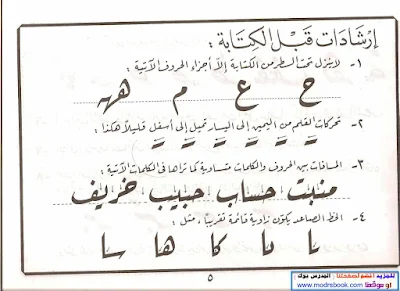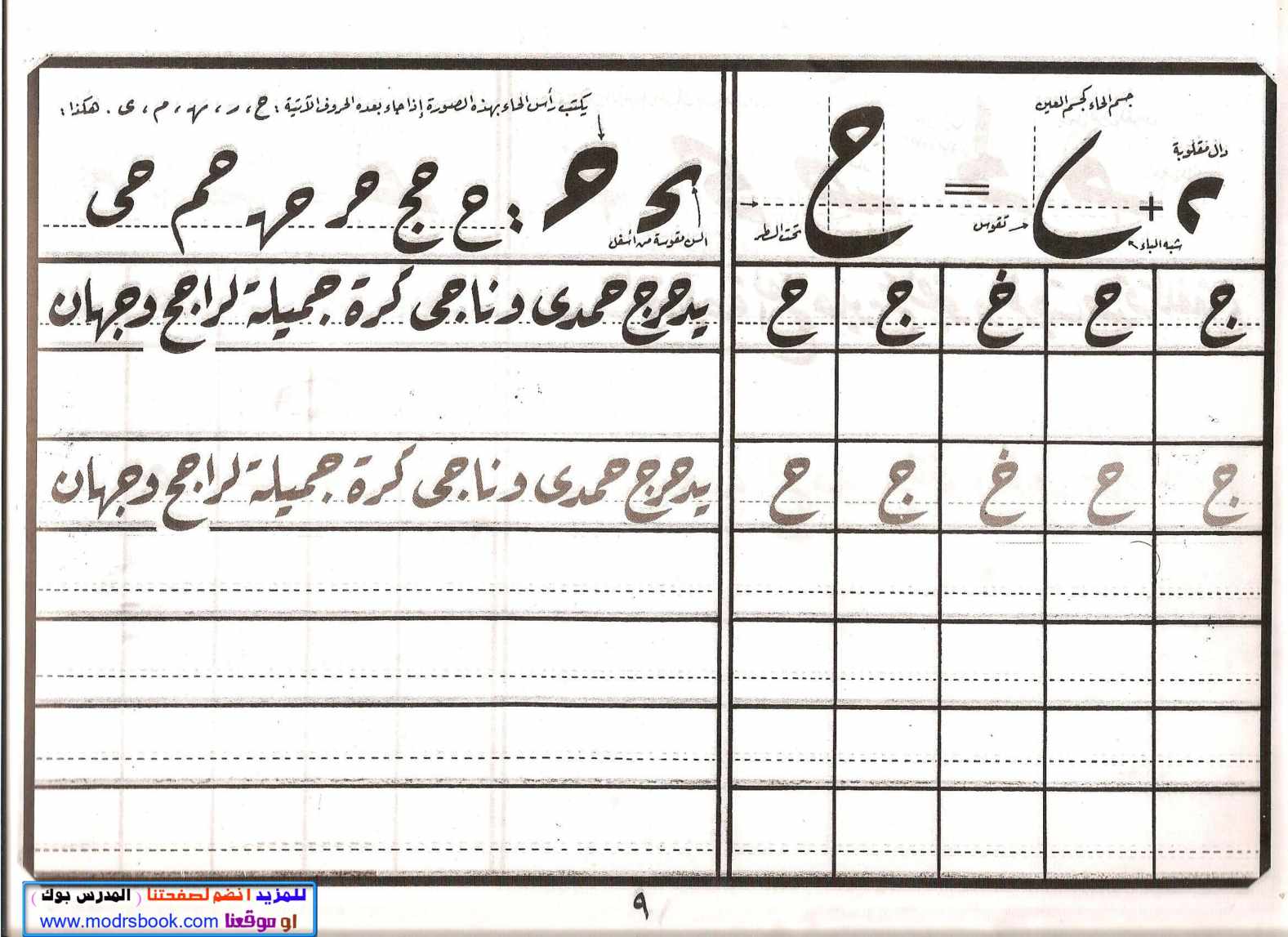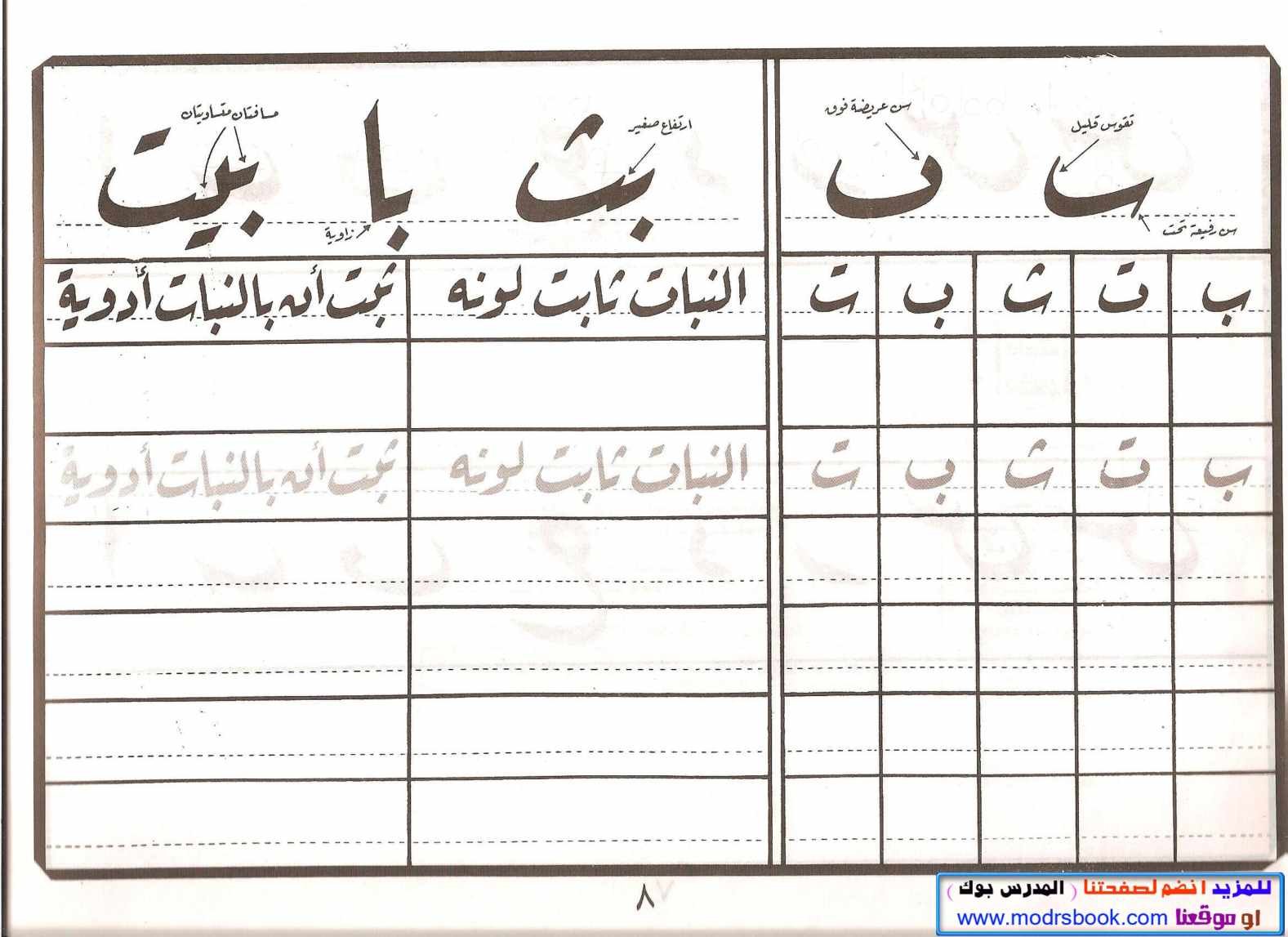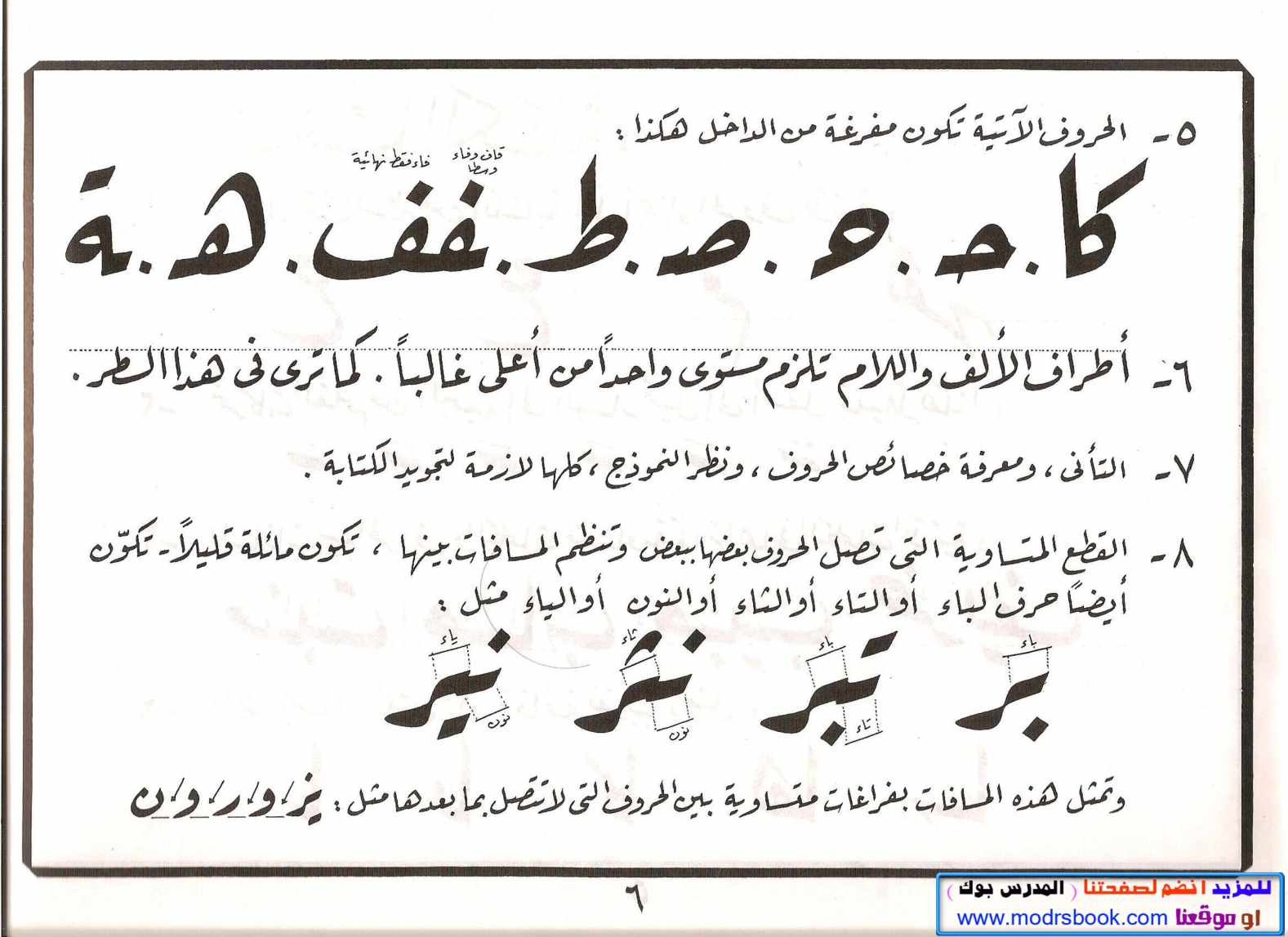
تحسين خط الرقعة في الكتابة العادية
يعاني الكثير منا من سوء خطه ويحتاج الي تحسين خطه في الكتابة سواء بالرصاص أو بالجاف ولعل من أجمل الخطوط وأسهلها هو خط الرقعة وسوف نعرض لكم اليوم كتاب رائع من اعداد / أحمد صبري زايد يتناول فيه كيفية تحسين وتدريس خط الرقعه بطريقة سهله وبسيطه لكل المتعلمين
مميزات كتاب تحسين خط الرقعة
- عرض ارشادات قبل الكتابة لتحسين الخط مثل :
- الحروف التي لاتنزل منها الا اجزاء تحت السطر
- تحركات القلم من اليمين إلي اليسار
- المسافات بين الحروف والكلمات
- الخط الصاعد وكيفية التعامل معه
- الحروف المفرغة من الداخل
- أطراف الالف واللام وكيفية التعامل معها
بعدها يعرض الكتاب الحروف وكيفية كتابتها حرف حرف وطرق التعامل معها لتحسين خطك
- مؤلف الكتاب أ / أحمد صبري زايد